Чертёжный шрифт
| Стиль | рублёный, пропорциональный, минималистичный |
| Классификация | технический |
| Использование | в чертежах |
| Набор символов | русский, латинский, греческий алфавиты, технические символы |
Чертёжный шрифт — рукописный и компьютерный шрифт, который применяется для оформления чертежей и других технических документов. Шрифт стандартизован, его описывает международный стандарт ISO 3098 «Technical product documentation — Lettering» (до 2000 года — DIN 6776-1 «Technische Zeichnungen — Beschriftung, Schriftzeichen») и такие национальные стандарты, как, например, ГОСТ 2.304-81 «Единая система конструкторской документации. Шрифты чертежные». Надписи чертёжным шрифтом могут выполняться от руки с использованием прямоугольной или наклонной сетки, могут использоваться трафареты и сухой перенос, а также компьютерный набор.[1]
Согласно требованиям системы стандартов ЕСКД все надписи на чертежах должны быть выполнены чертёжным шрифтом по ГОСТ 2.304-81, а в текстовых документах чертёжный шрифт должен использоваться при рукописном способе выполнения[2].
Стандарт устанавливает высоту и ширину символов, толщину линии, расстояния между символами строками и словами.
Стандарты ISO 3098 и ГОСТ 2.304-81 определяют написание для латинского, кириллического и греческого алфавитов, арабских и римских цифр.
История
До 1840-х годов надписи на чертежах в России выполнялись теми же почерками, что и обычные документы, с редким применением букв гражданской печати[3]. После этого на чертежах появляются художественные шрифты (готические, славянские, курсивы и др.)[3], которые в 1870-е годы во многом сменила разработанная Фридрихом Зённекеном модификация старинного французского шрифта «рондо» (Rundschrift)[4]. С увеличением производства чертежей и распространением светокопирования и синек вскрылись недостатки шрифта рондо: он был труден для исполнения, а его тонкие элементы в мелком кегле исчезали на копиях[3].
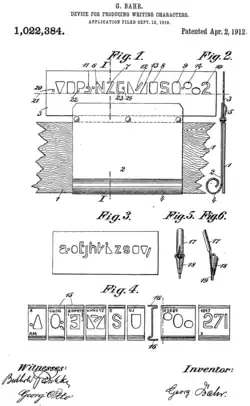
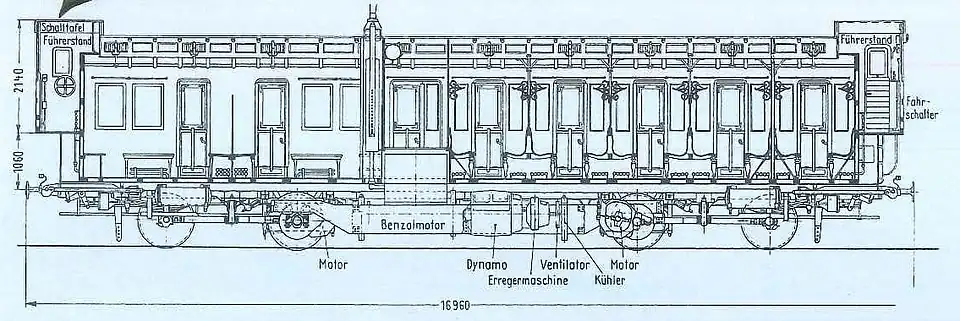
В 1895 году американец Чарльз Рейнхардт предложил использовать для фотокопируемых рабочих чертежей максимально простой и практичный шрифт с одинаковой толщиной штрихов[5][6]. В 1900-е годы стали появляться целлулоидные шрифтовые трафареты, которые позволили легко писать на чертежах буквы и цифры, отвечающие требованиям простоты и минимальной контрастности (малого контраста)[4]. Прусские железные дороги приняли стандарт Musterzeichnung IV 44 на шрифты для надписей на вагонах, схемах и чертежах, а вскоре также и вывесок на станциях[7]. В 1919 году на основе железнодорожного стандарта основанный двумя годами ранее Комитет по стандартизации немецкой промышленности установил первые в мире стандарты DI-Norm (DIN) 16 для наклонного и DIN 17 для прямого чертёжных шрифтов[7].
В 1928 году Комитет по стандартизации при Совете труда и обороны СССР опубликовал разработанный годом ранее Комиссией по нормализации чертежей при ВСНХ общесоюзный стандарт (ОСТ) 353 с наклонным (75°) «нормальным» чертёжным шрифтом, который имел рекомендательный характер и изначально не получил широкого распространения[3]. После введения в шрифт «круглых» строчных букв он был в 1934 году утверждён ОСТ ВКС 7535 в качестве обязательного для всех чертежей в машиностроении и несмотря на внесение незначительных изменений в 1941 (ОСТ 7535—39), 1946 (ГОСТ 3554—46), 1953 (ГОСТ 3554—52) и 1959 (ГОСТ 3554—59) годах просуществовал почти в исходном виде до введения ЕСКД в 1968 году.
Стандарты
Международный стандарт ISO 3098 состоит из шести частей под общим наименованием «Документация техническая на продукцию. Шрифт для надписей и обозначений»[8]
- ISO 3098-1:2015 «Technical product documentation — Lettering — Part 1: General requirements» («Часть 1. Общие требования»)
- ISO 3098-2:2000 «Technical product documentation — Lettering — Part 2: Latin alphabet, numerals and marks» («Часть 2. Латинский алфавит, цифры и знаки»)
- ISO 3098-3:2000 «Technical product documentation — Lettering — Part 3: Greek alphabet» («Часть 3. Греческий алфавит»)
- ISO 3098-4:2000 «Technical product documentation — Lettering — Part 4: Diacritical and particular marks for the Latin alphabet» («Часть 4. Диакритические и специальные знаки для латинского алфавита»)
- ISO 3098-5:1997 «Technical product documentation — Lettering — Part 5: CAD lettering of the Latin alphabet, numerals and marks» («Часть 5. Шрифт из букв латинского алфавита, цифр и знаков для систем автоматизированного проектирования»)
- ISO 3098-6:2000 «Technical product documentation — Lettering — Part 6: Cyrillic alphabet» («Часть 6. Кириллица»)
Межгосударственный стандарт ГОСТ 2.304-81 был введён в действие в 1982 году и заменяет предшествовавший стандарт ГОСТ 2.304-68.
Стандарт Немецкого института стандартизации DIN 6776-1 «Чертежи технические. Надписи, шрифтовые знаки» в ноябре 2000 года был заменен на национальный стандарт DIN EN ISO 3098.
Размеры
Высота шрифта
Размером шрифта называется высота прописных (заглавных) букв в миллиметрах. Размер (высота) шрифта обозначается буквой h.
Стандарт устанавливает следующие размеры шрифта: 1,8; 2,5; 3,5; 5; 7; 10; 14; 20; 28; 40 (каждый следующий размер больше предыдущего приблизительного в раз). Размер 1,8 не рекомендуется, но допускается. Размеры 1,8 и 2,5 не допускаются, если чертёж выполняется карандашом. Для стандартного чертежа предпочтительными являются размеры 3,5; 5 и 7. Высота строчных букв равна предыдущему размеру шрифта. Так, если размер шрифта — 10, то высота прописных букв — 10 мм, а высота строчных —7.
Выносные элементы
Термин «высота шрифта» не учитывает выносных элементов символов, которые выполняются за счёт промежутков между строками. В кириллице выносные элементы имеют прописные буквы Д, Й, Ц, Щ и строчные буквы (буква Ё в ГОСТ 2.304-81 не упоминается).